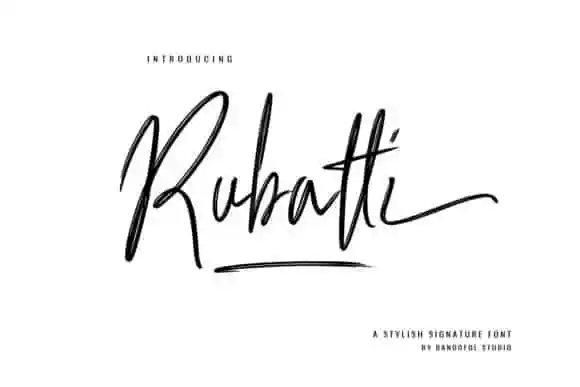
Rubatti Brush Font – Download Grátis
A Rubatti Brush Font é uma fonte script fresca e natural ideal para trabalhos visuais criativos. Desenhada pela Bandofol Studio, essa fonte foi criada com técnicas manuais que produzem um texto com textura de pincel natural, perfeitamente adequado para várias aplicações, incluindo revistas, identidades de marca, promoções, embalagens e muito mais. Com letras maiúsculas, minúsculas, números e sinais de pontuação, essa fonte apresenta várias variações em cada caractere, fazendo-a perfeita para uso em um amplo espectro de projetos. Seu design único e seu texto branco suave criam uma aparência elegante e moderna, tornando-se uma escolha ótima para aqueles que buscam uma fonte única e imponente para seus projetos visuais.